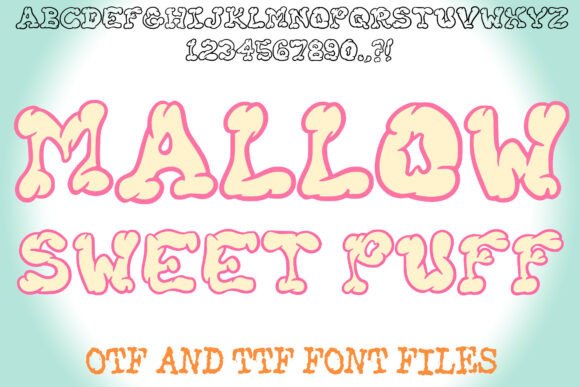
Mallow Sweet Puff
適切なデザイン要素を見つけるのは難しい場合がありますが、Mallow Sweet Puffは作品を即座に引き立てる優れたコレクションを提供します。
POD(オンデマンド印刷)製品、結婚式の招待状、またはソーシャルメディアのグラフィックを作成している場合でも、Mallow Sweet Puffは理想的です。